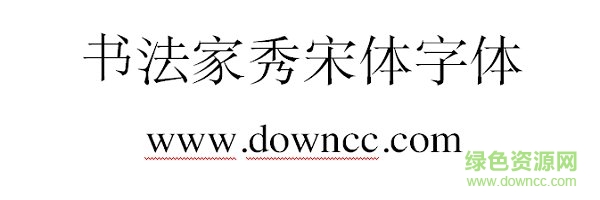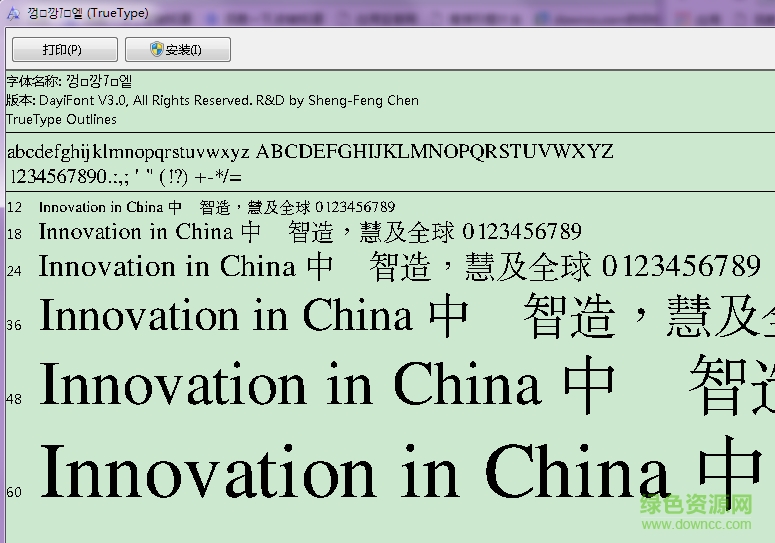
書法家秀宋體是書法家字體庫中非常大氣的字體,該字體簡單偏細,是我們生活中用的比較多的字體,書寫簡單,我們可以正確的辨別,給人以清爽的感覺,看了讓人喜歡。需要的朋友趕緊來綠色資源網(wǎng)下載吧
書法家秀宋體一款比較漂亮的書法家字體、宋體字體,就目前來看,該字體的使用范圍比較大,需要的小伙伴比較多,它與其他的字體相比較的話就是更非常的正規(guī),四四方方的。